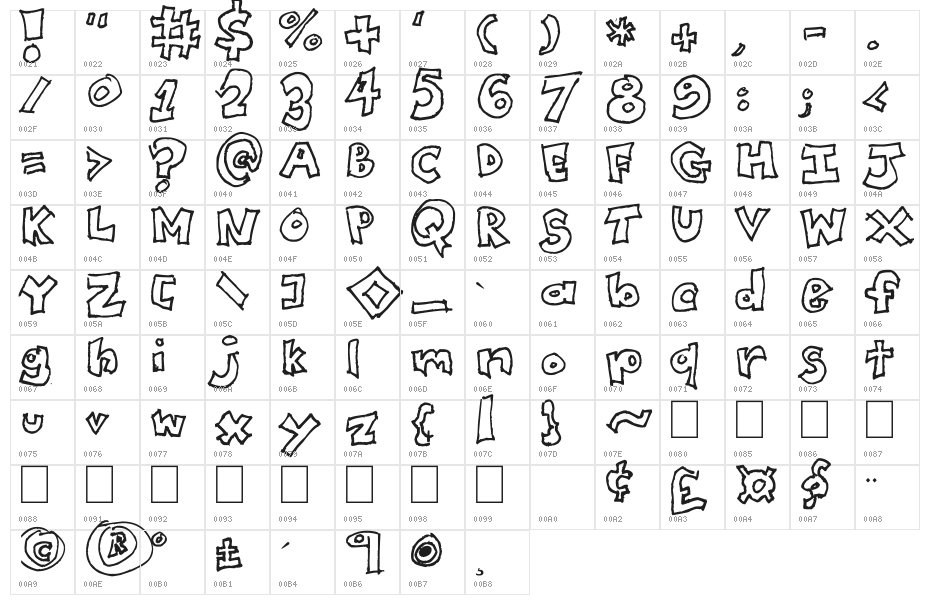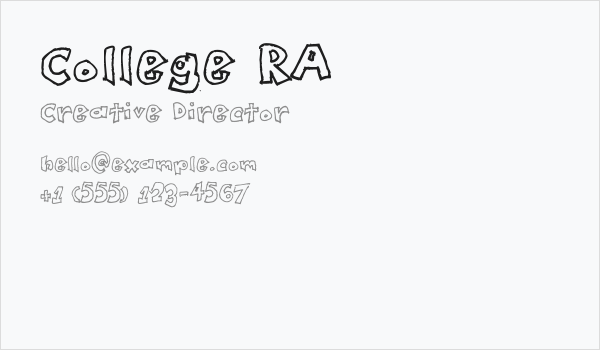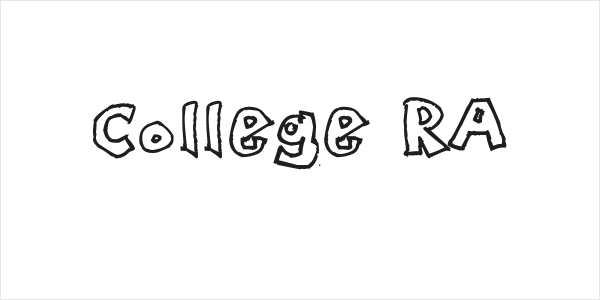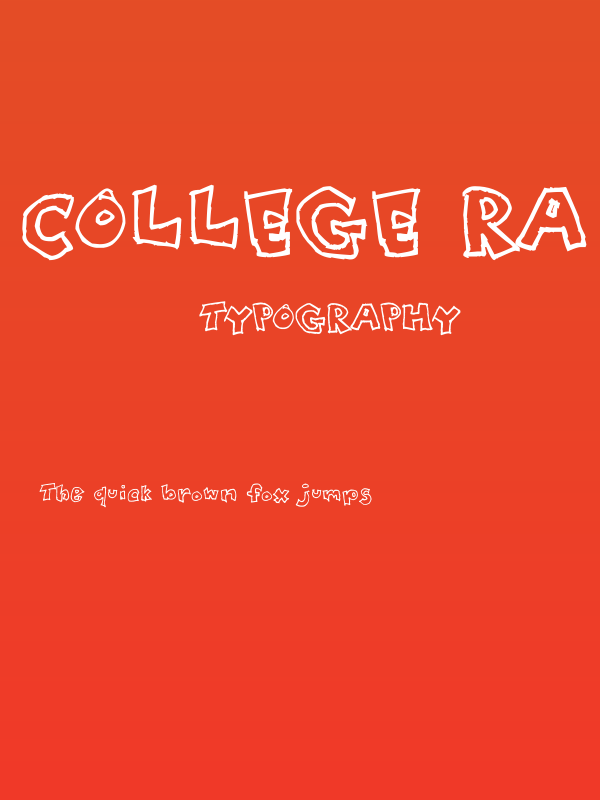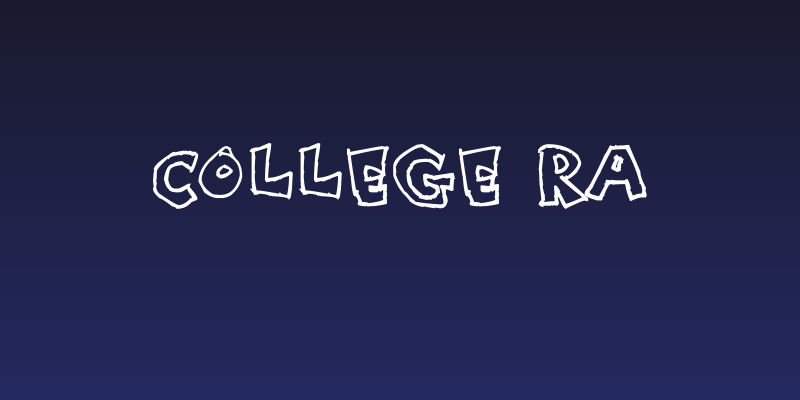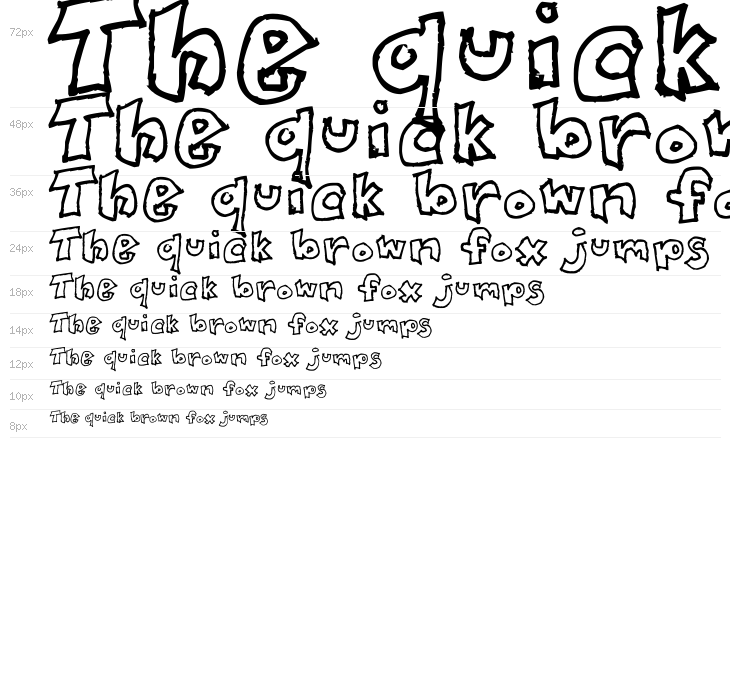
College RA Font
| Style général | Playful, Whimsical |
| Projets proposés | Ideal for children's books, comic strips, playful branding, and party invitations. |